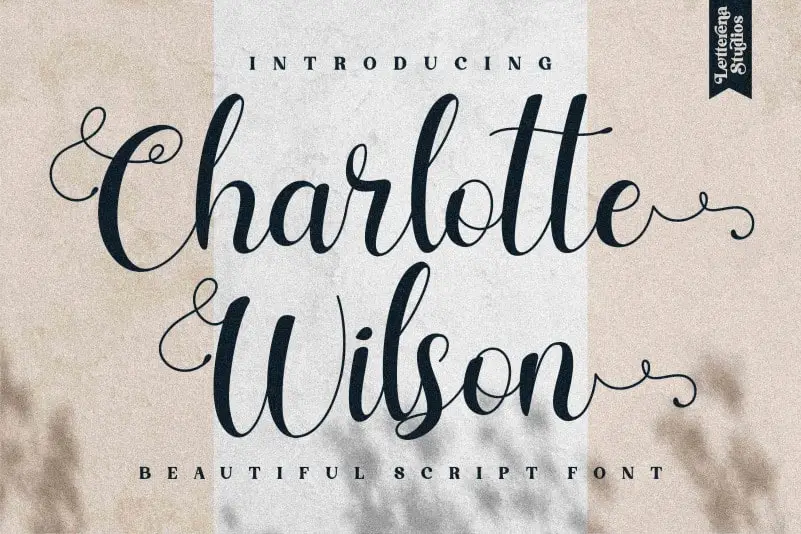
Charlotte Wilson Calligraphy Font – Download Grátis
Charlotte Wilson é uma elegante fonte de escrita à lápis que oferece contraste entre as letras finas e os desenhos delicados. Com seu estilo romântico, esta fonte atende a um amplo leque de projetos, incluindo logotipos, identidades corporativas, designs de móveis de casa, embalagens de produtos, taças para café, cartazes, sacolas de compras, camisetas, capas de livros, cartões de nome, convites, cartões de lembrança, rótulos, fotografia e até eventos especiais. A fonte foi codificada PUA, permitindo que você facilmente acesse os caracteres e desenhos disponíveis desta maneira. Este é um recurso de design ideal para aqueles buscando uma pitada sofisticada e delicada em seus trabalhos visuais. Charlotte Wilson é perfeita para adicionar um toque de personalidade e criatividade, tornando-se a escolha perfeita para seu próximo projeto visual.